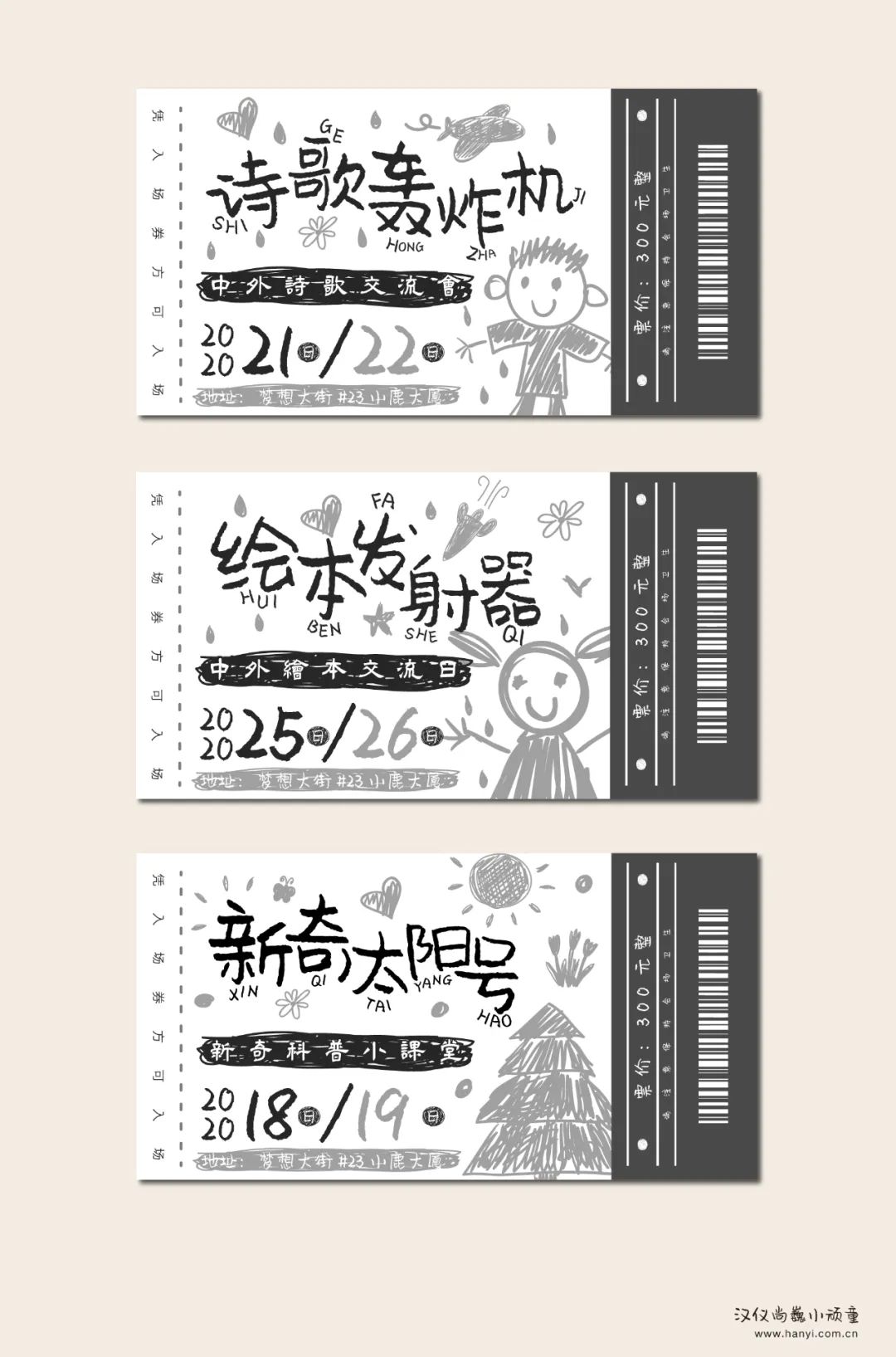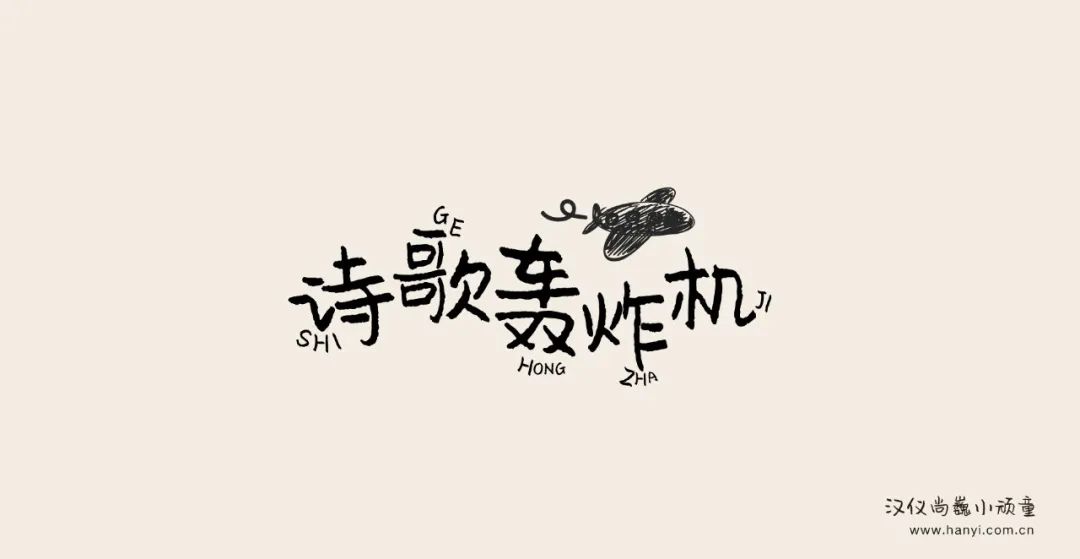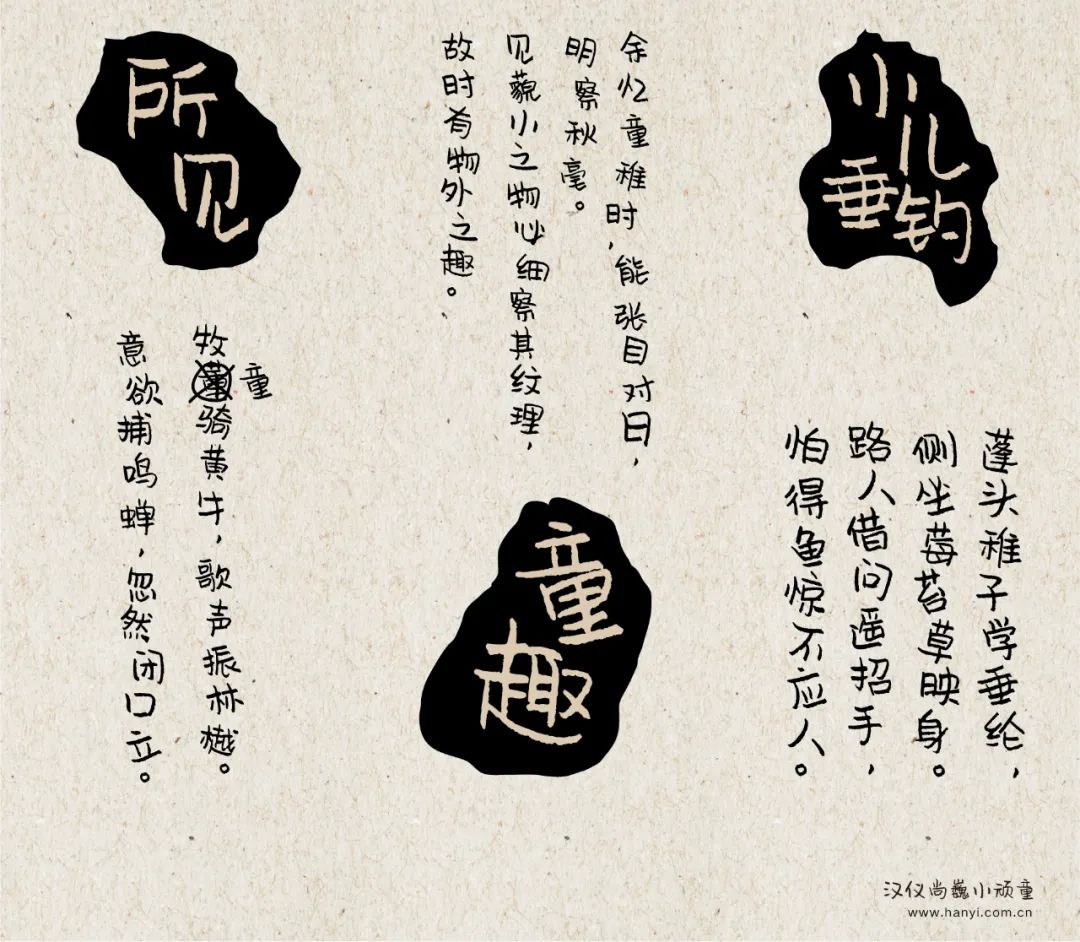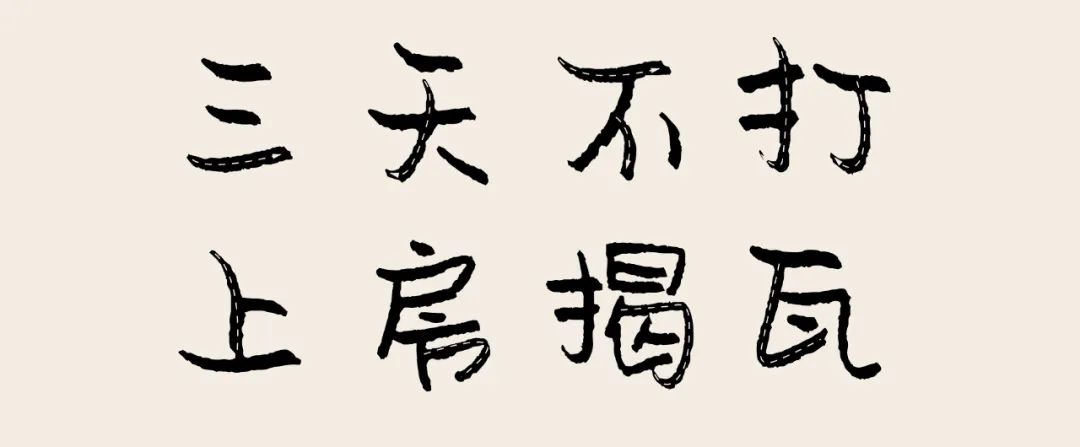
汉仪尚巍小顽童 | 一款非常具有亲和力的手写字体
它的笔画转折圆润,有着细腻的弧线曲度,使充满童趣的手写体更加有趣。
汉仪尚巍小顽童保留了笔墨与纸张接触后富有变化的纹理,多了一份天真质朴。它的西文设计也融入了中文书法的手写方式,笔触丰富,运笔流畅,手写感强,弹性十足。中西文搭配使用时,效果更佳。
字体应用